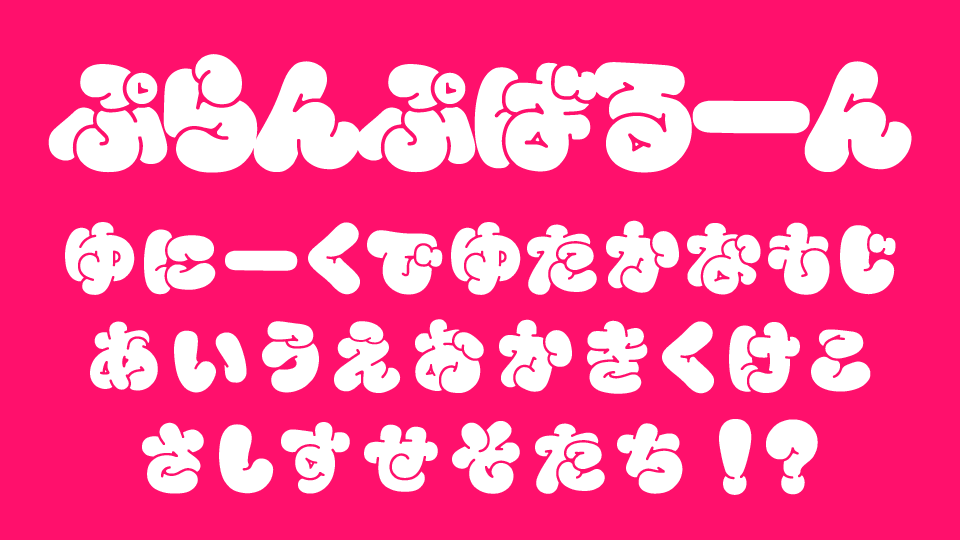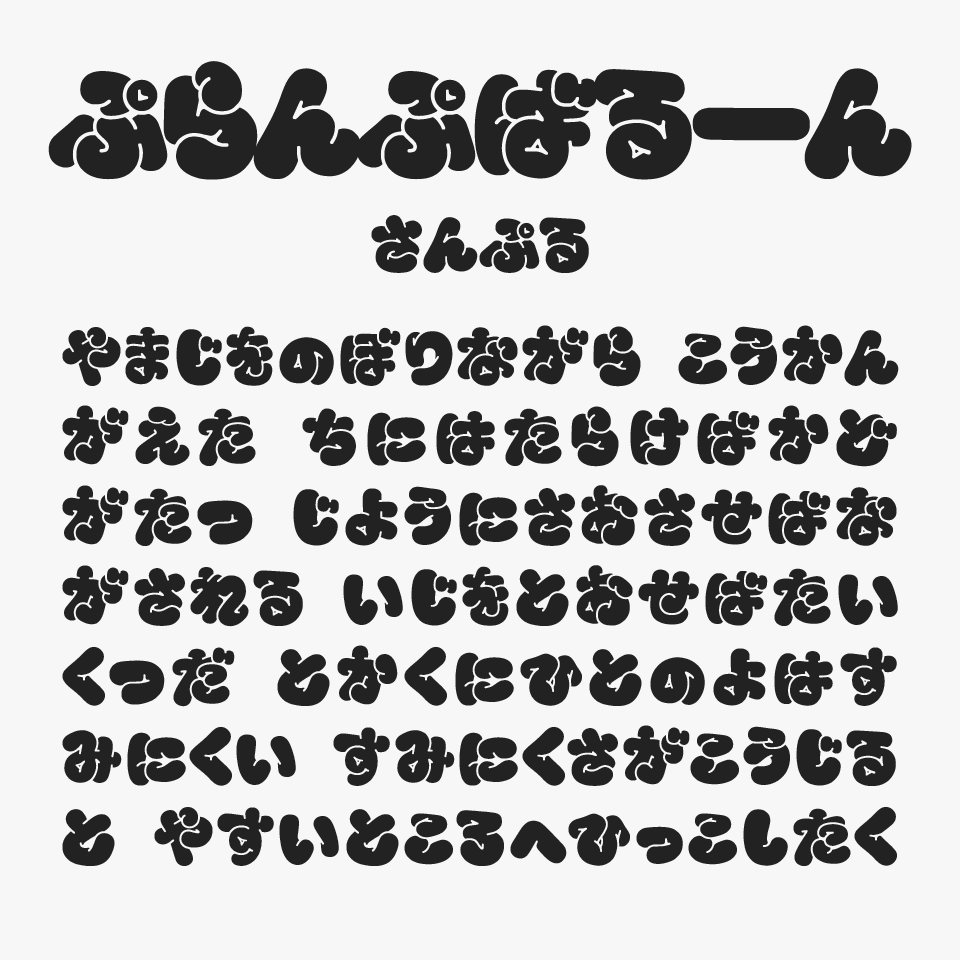
ぷらんぷばるーんフォントは、極端に丸みを強調したシルエットと、パンパンに膨らんだ風船のような文字形が特徴的なデザインフォントです。
文字の内部に入った小さなハイライト風の抜けが独特で、ぷにっとした質感やぷくっと膨らんだ柔らかさを感じさせるデザインです。
文字そのものがキャラクターのように見えるほど個性が強く、見た瞬間に楽しい空気感を伝えてくれるフォントです。
ぷらんぷばるーん